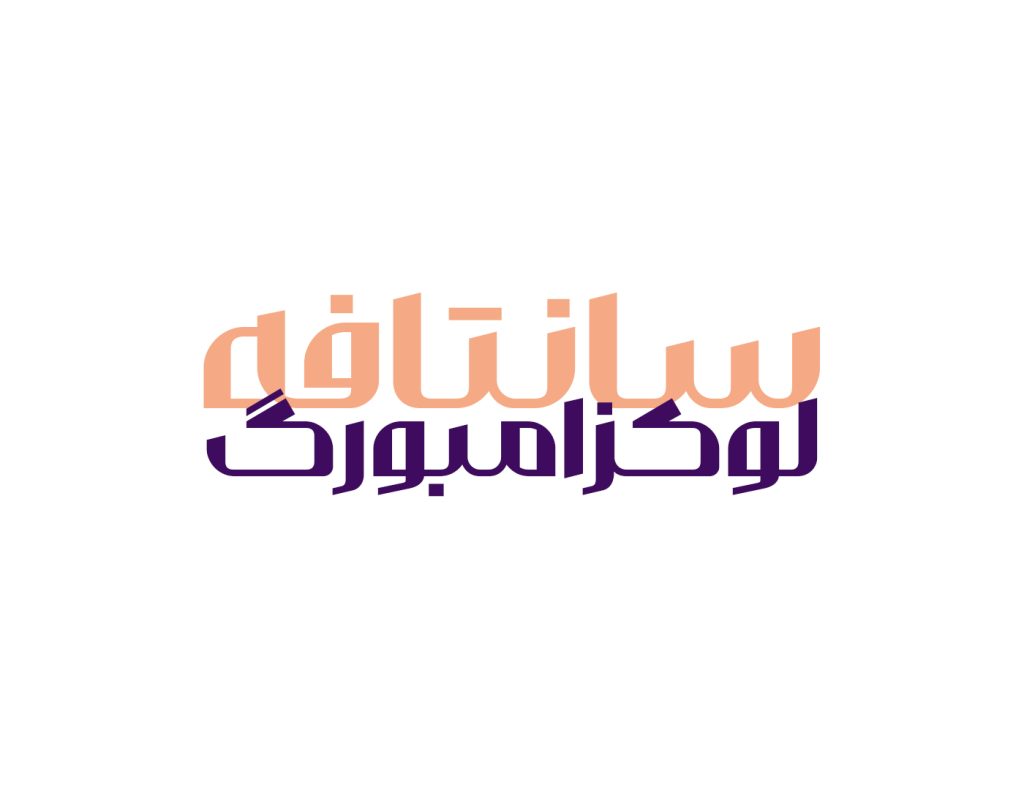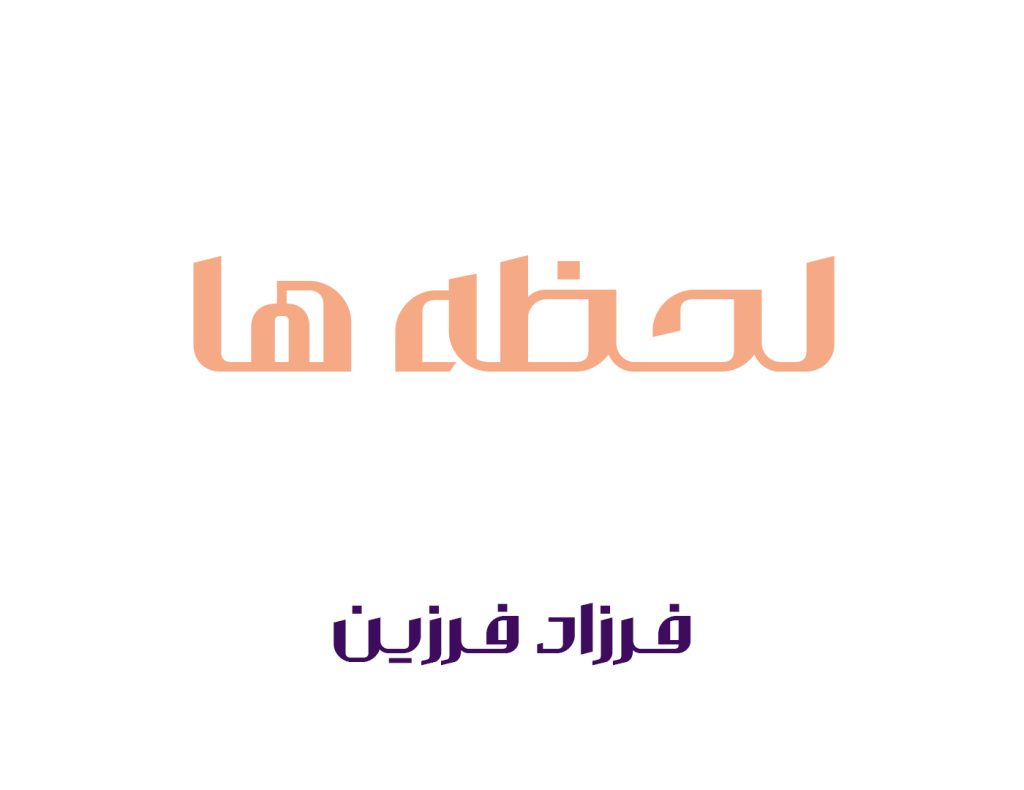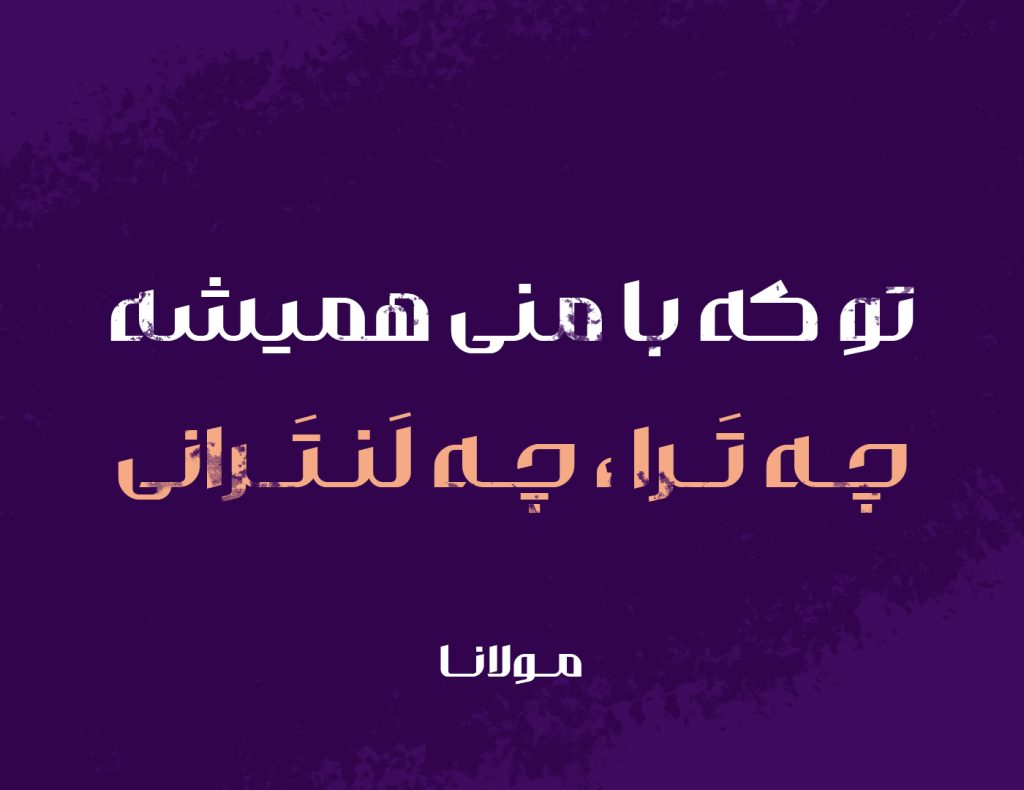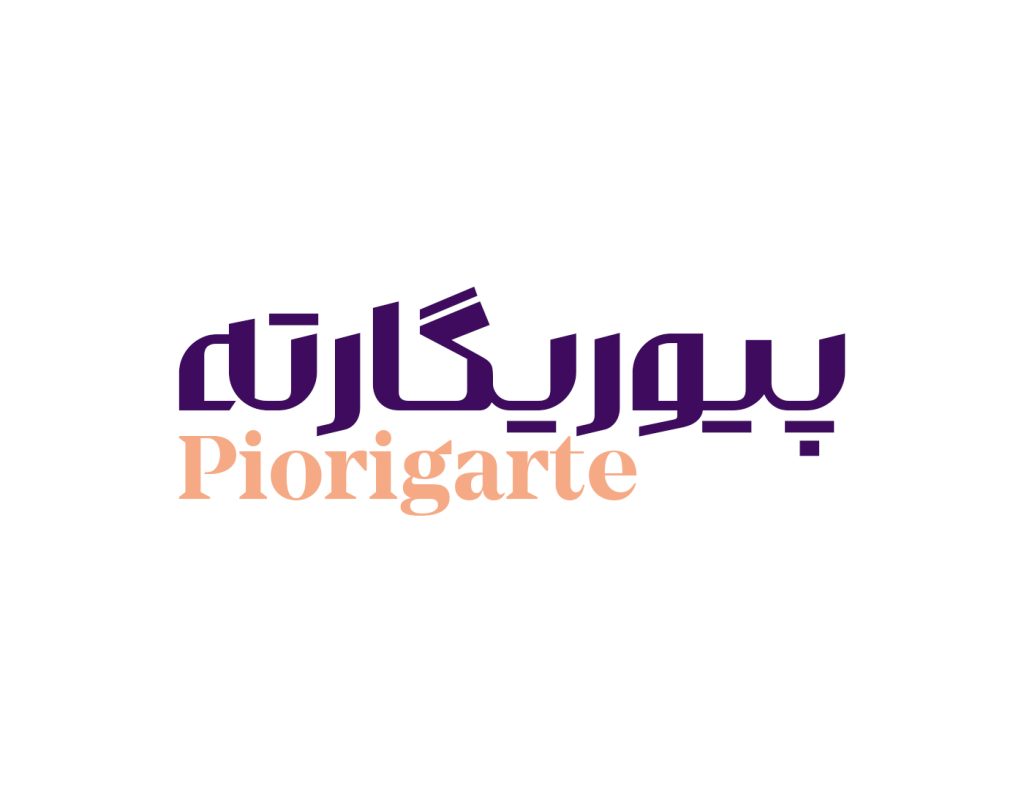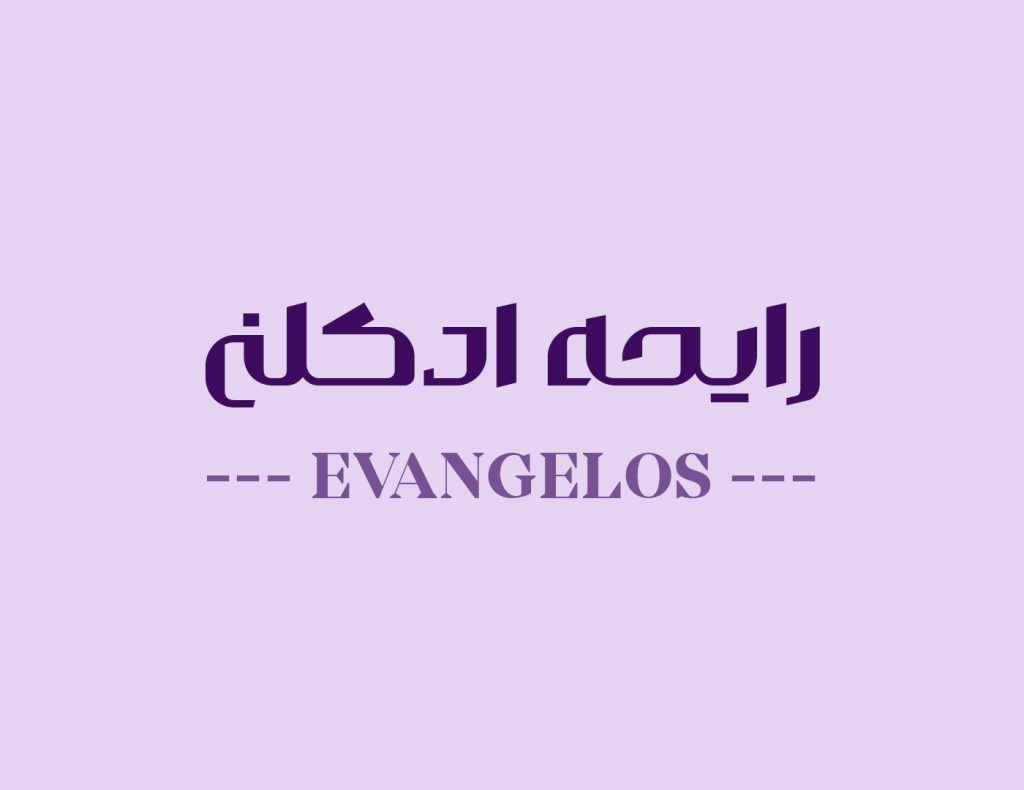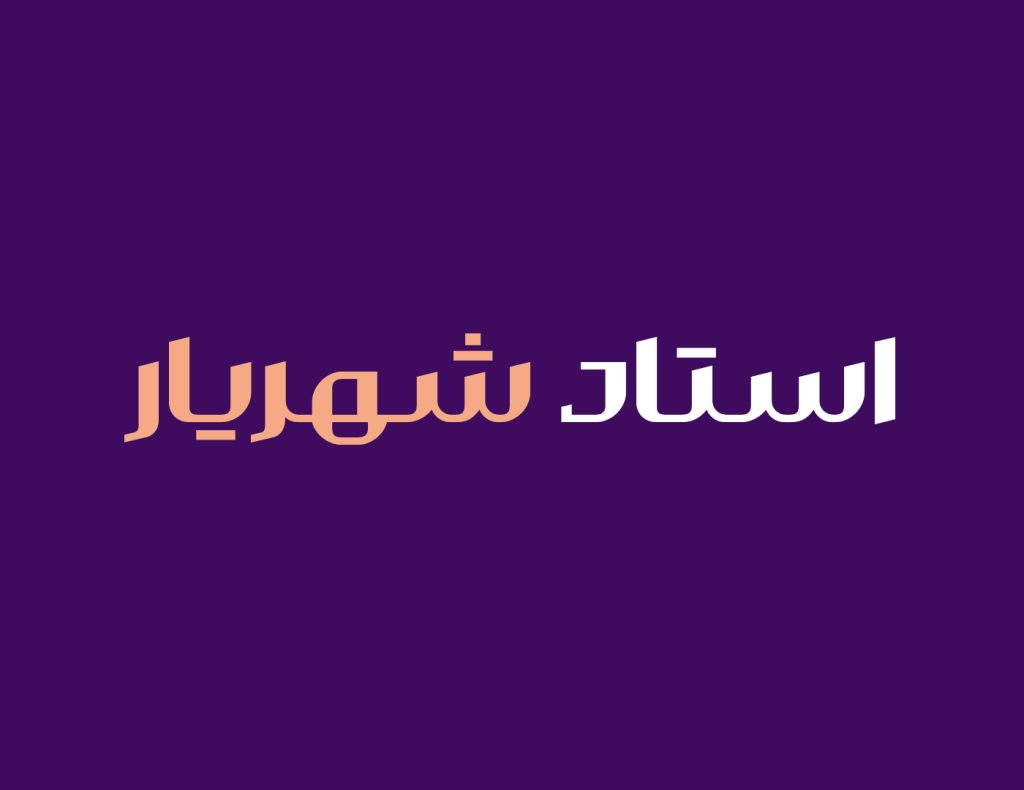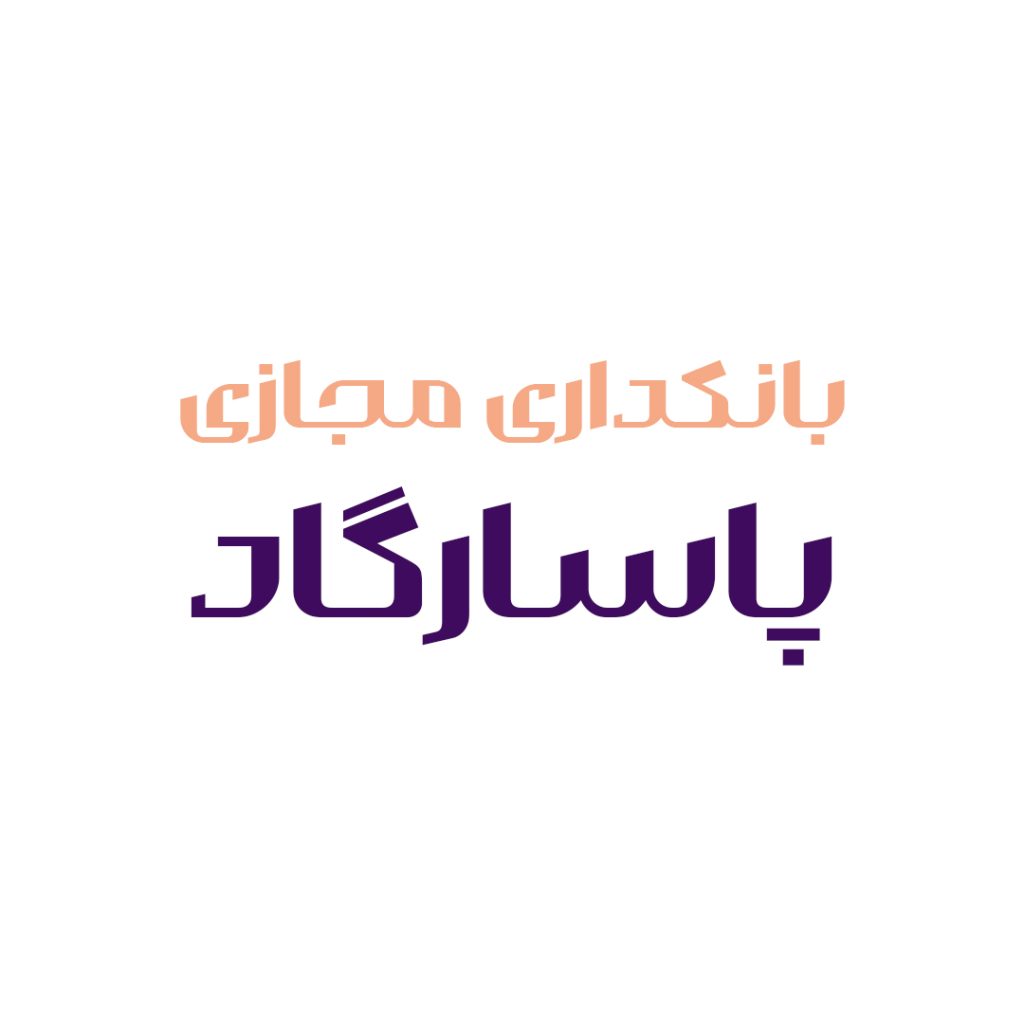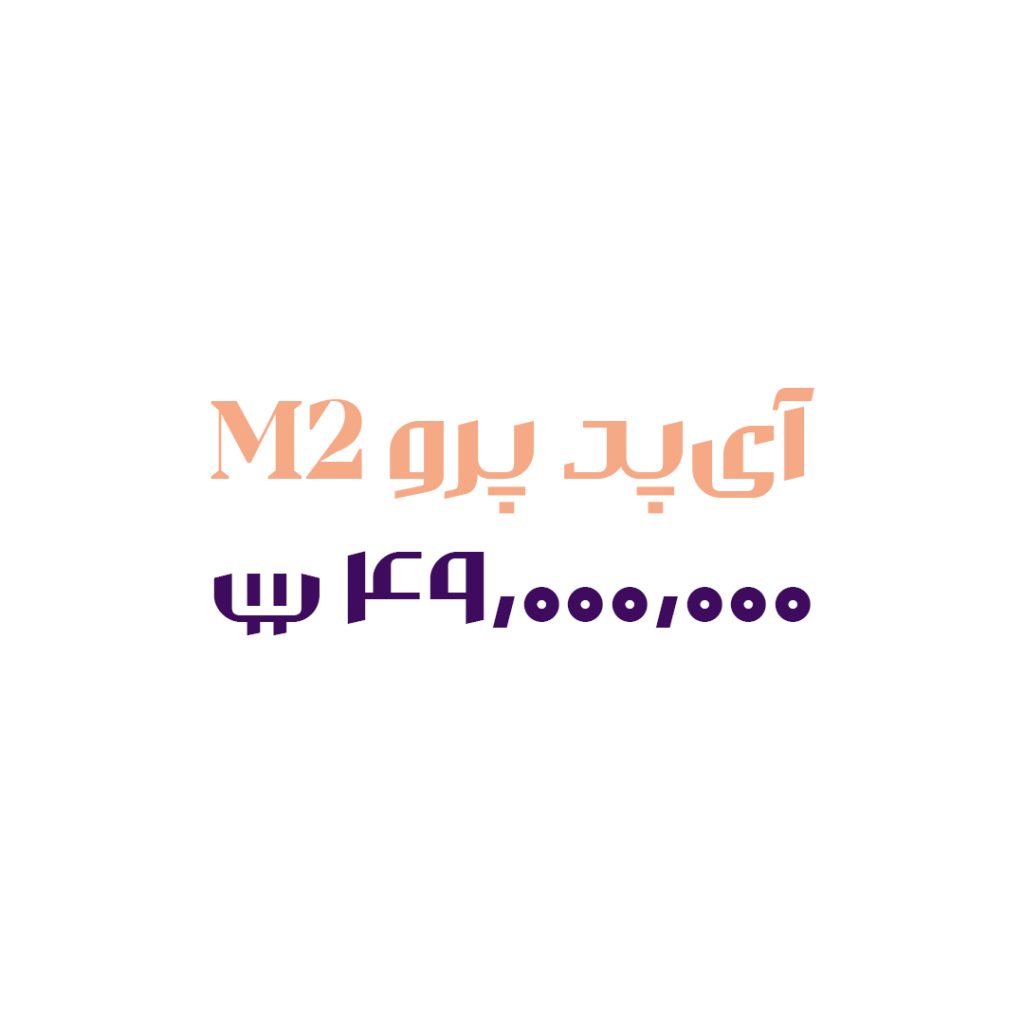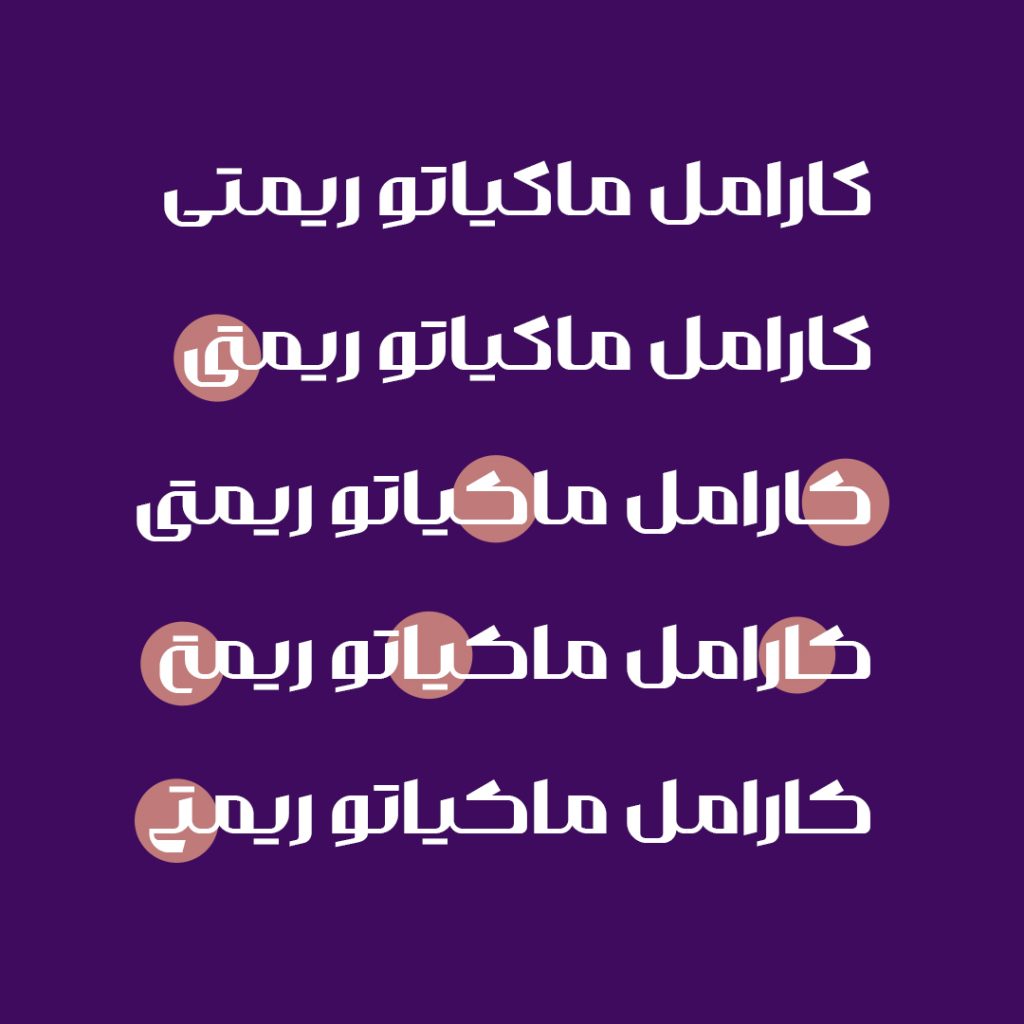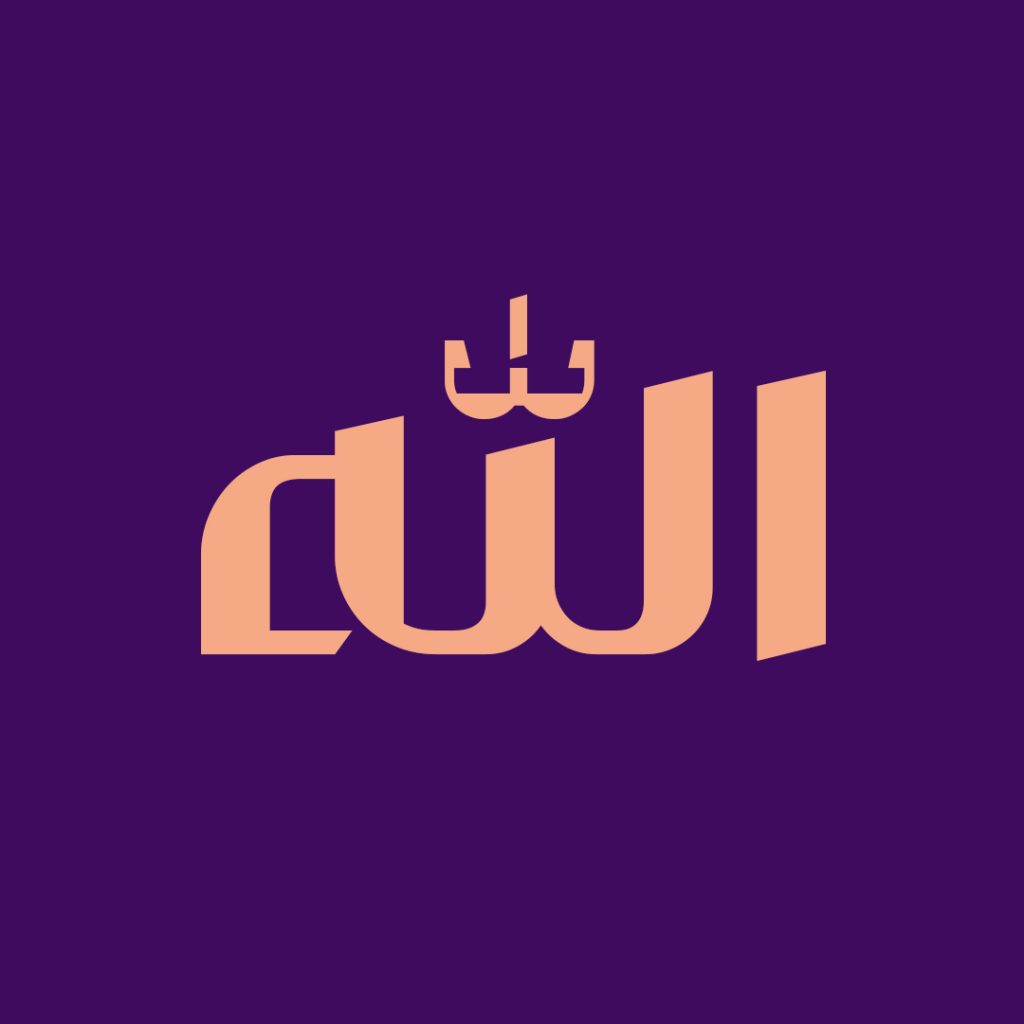
فونت والمان قلمی هندسی با ظاهری منحصر به فرد و خاص مناسب برای طراحی تیتر ها و عناوین و لوگو تایپ ها و .. می باشد. با ما همراه باشید تا این تایپ فیس نمایشی را به شما عزیزان معرفی کنیم.
فونت والمان
فونت والمان با تلاش و همت طراحان آقای حسین حیدری و مهدی ارشادی ایجاد و متولد شده است. والمان تشکیل شده از روند طراحی برای یک لوگو تایپ برای برندی بوده که بعد ها با گسترش به تمامی حروف و ترکیبات تبدیل به فونت و تایپ فیسی هندسی گشته است. همانگونه که مشخص است خطوط عمودی نسبت به خطوط افقی دارای پهنای ضخیم تر است.
این قلم تایپ فیسی مدرن و امروزی است. و فرم های طراحی آن اقتباسی از قلم های لاتین می باشد . کاهش ارتفاع خطوط کرسی سبب فشرده گی و انسجام درونی بیشتر در والمان شده است. کنتراست سطحی آن نیز منجر به افزایش بیشتر ویژگی نمایشی و جذابیت آن گشته است.
کاربرد والمان برای تیتر ها و لوگو تایپ ها
همانطور که در ابتدا اشاره شد والمان اساسا در طراحی مسیر یک لوگو تایپ ایجاد و توسعه یافته است . ظاهر منحصر به فرد و خاص فرم های ساختاری این قلم مناسب برای طراحی لوگو تایپ می باشد می توانید با نرم افزار های طراحی از جمله آدوبی ایلسترتور و فتوشاپ نسبت به ساخت و ایجاد لوگو تایپ های سفارشی خود اقدام نمائید.
والمان مناسب برای نوشته های بلند و ریز نیست و کاربرد آن برای متون کوتاه و عناوین و تیتر هاست. می توان از آن برای طراحی بسته بندی، تابلو فروشگاه و انواع تبلیغات تجاری که می‌خواهید لوکس و مدرن به نظر برسد استفاده کنید. شخصیت مدرن و لوکس والمان که جسور و جدی نیز می باشد بسیار مناسب برای تبلیغات در پست های شبکه های مجازی و وب سایت ها می باشد علاوه بر اینکه این قلم دارای ویژگی نمایشی بالایی هم می باشد. که نگاه بینندگان و مخاطبین را به خود جذب می کند.
پشتیبانی قلم والمان از ترکیبات جایگزین
از دیگر ویژگی های این تایپ فیس پشتیبانی از ترکیبات و حروف جایگزین است . که سبب خلق تنوع و دوری از رخوت در طراحی و نوشته ها می شود و دست طراحان را برای ایجاد تنوع و زیبایی بیشتر باز می گذارد. پس از دانلود این محصول  می توانید در بسته راهنمای آن نحوه استفاده از این لیگچر ها و ترکیبات را مشاهده نمائید.